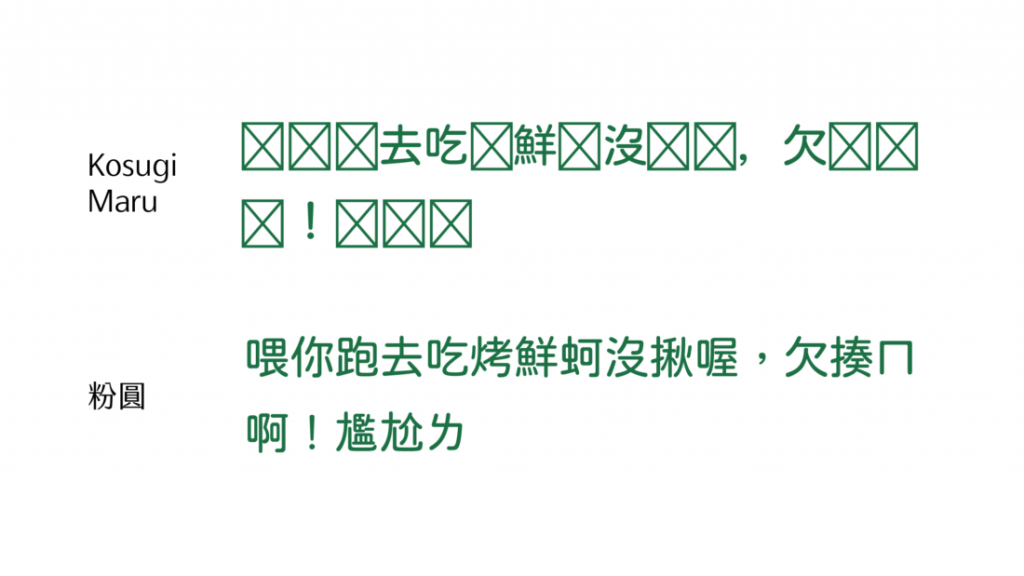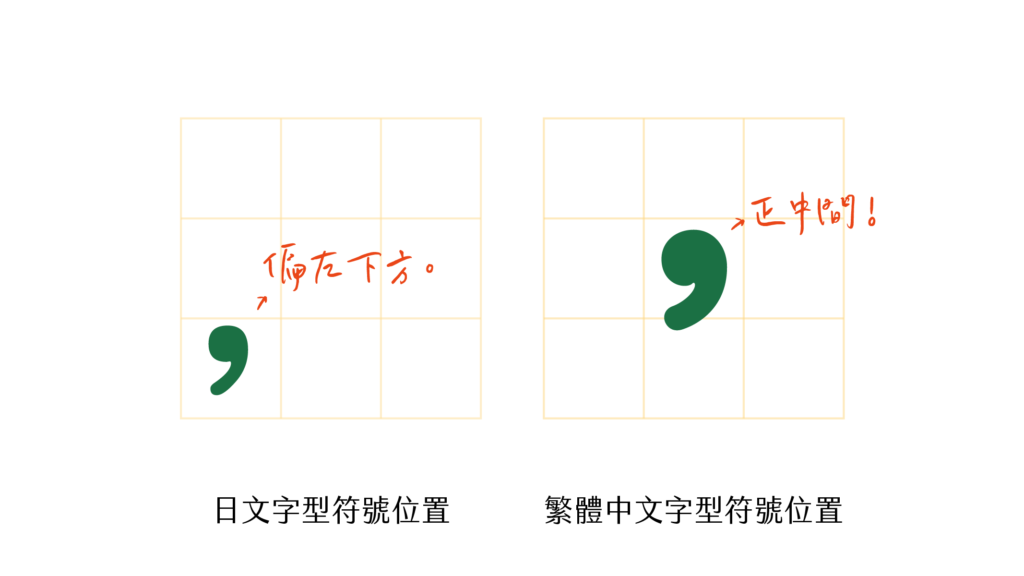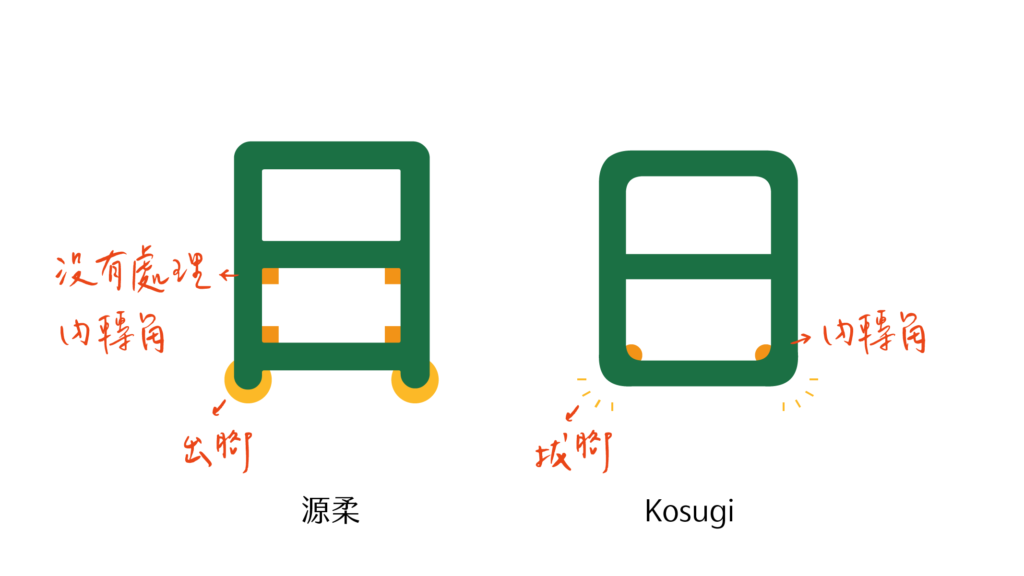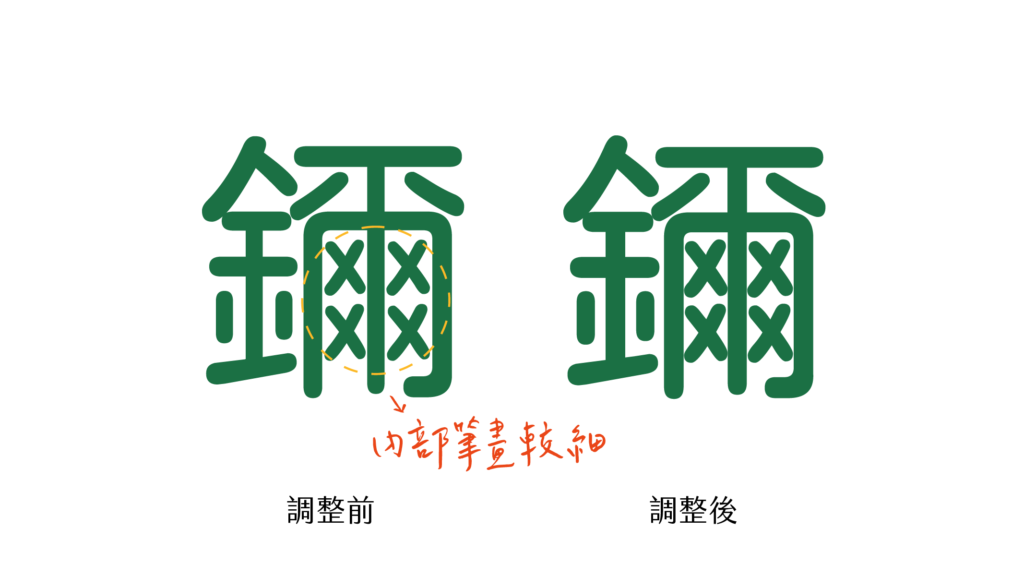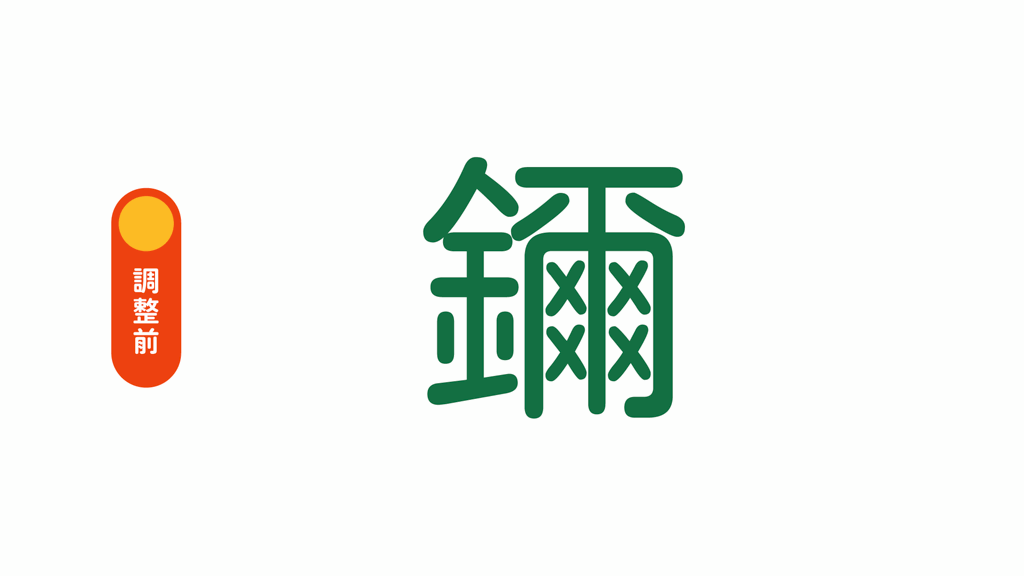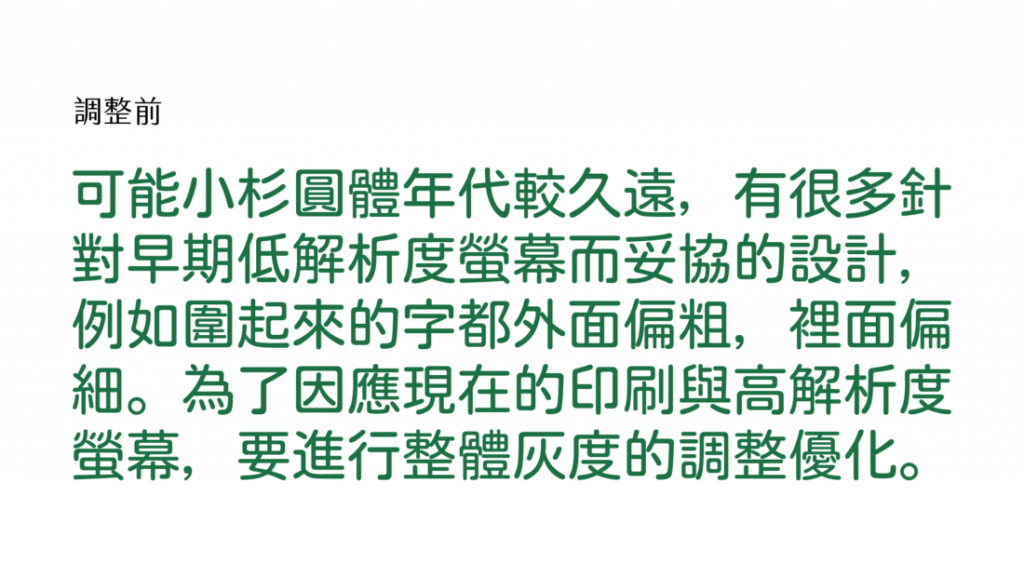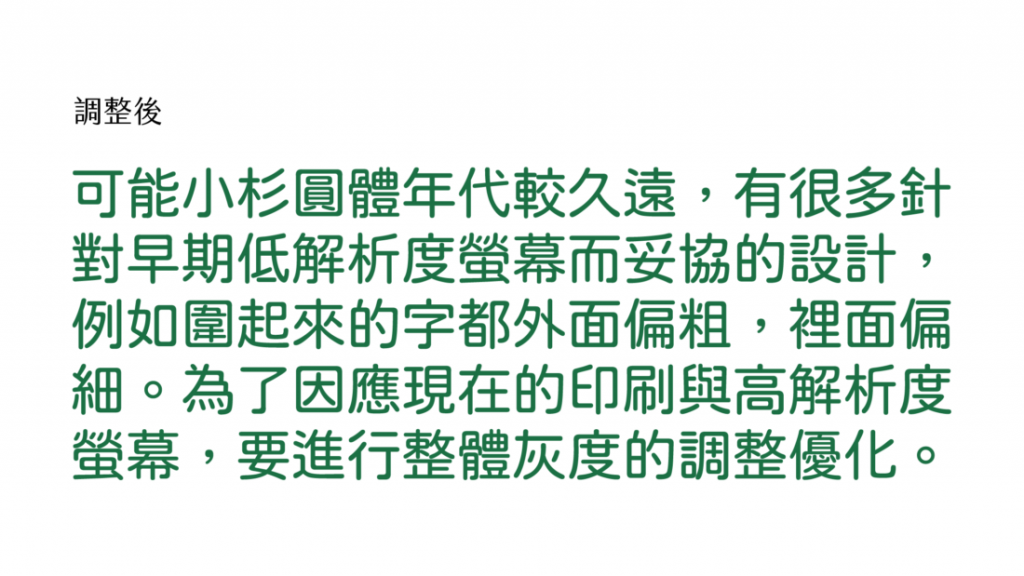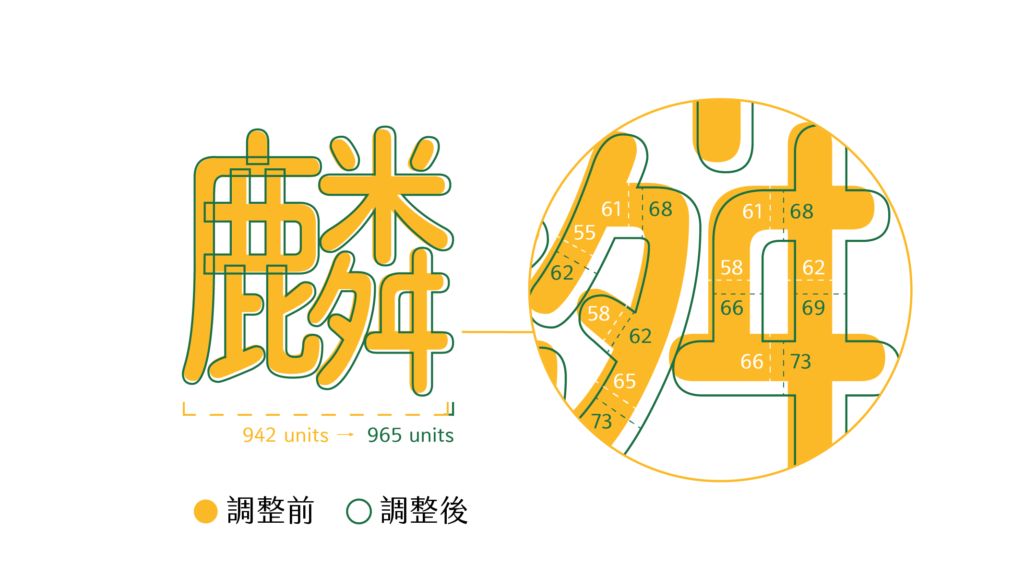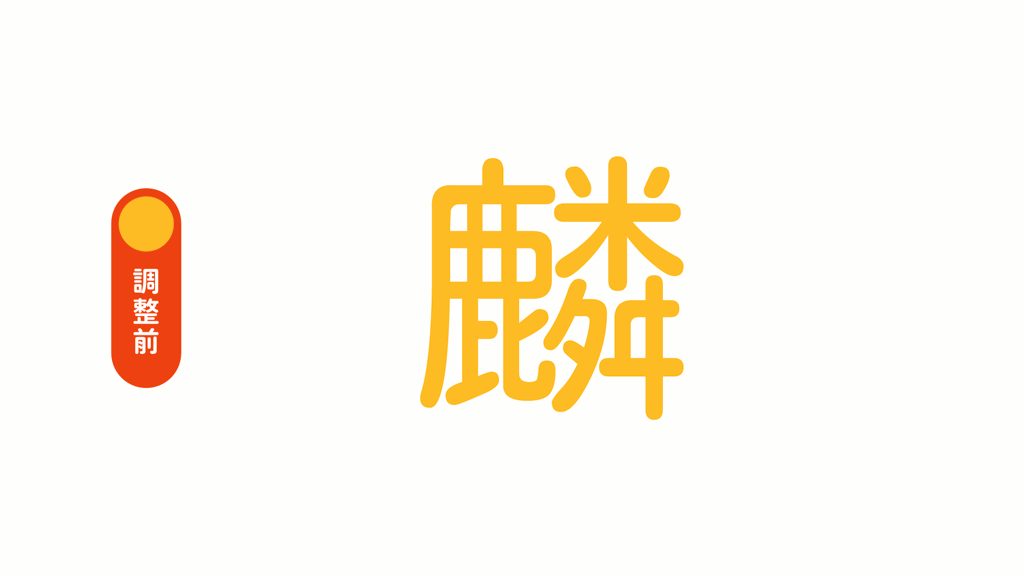
现在开源圆体字型屈指可数,符合台湾排版需求的更是凤毛麟角。 中国台湾字体公司金萱字型成功后,为回馈社会,他们承诺为台湾使用者优化一套开源字型作品。
2019年,JustFont 终于提出了“粉圆计划”,将会基于现已开源的日本Motoya公司的 小杉圆体进行改造、升级成新的开源字型粉圆字体。并已于2020年3月14日15时09分(圆周率日3.14159)开放下载。
粉圆字体在原日文字型基础上,额外设计了1,477个中国台湾常用字、注音符号与台罗拼音,并修订排版设定,以适应台湾的使用需求。更改进了灰度品质,让排版更美丽!
简单来说,粉圆字体改了什么?
粉圆字体做一套适合台湾使用者排版的、品质良好的开源圆体。这包含调整标点符号的位置,新增很多台湾繁体中文会用到的字,还把原本汉字的品质变得更好。
1、小杉圆体中文字体较少,粉圆字体增加了1477个汉字。
2、因为日本的标点符号的习惯与中国不同,所以粉圆字体调整了符号的位置,并把添加正统圆体的特征。
3、修改字体的灰度,让字体达到理想状态。我们在修改这些字的“灰度”上花了很多时间。原本的字会常常出现部件笔画粗细不一致的现象,那我们就是必须手动去一笔一画的把粗细调整到比较理想的状态。这样一来就不会有些字比较黑,有些字又比较淡。
JustFont粉圆字体是基于Kosugi Maru改作,由JustFont设计师针对台湾日常应用加以优化的开源字型。欢迎大家自由应用、自由优化、自由改作!
“jf Open粉圆-1.1”是一款书写很新颖的字体,字体大方,适合各种设计作品使用!欢迎下载!